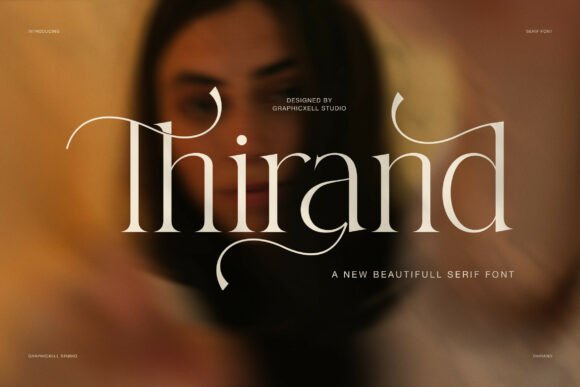
Thirand
Si buscas recursos de alta calidad como Thirand, este paquete premium es una opción fantástica para tus proyectos creativos.
Ya sea que estés creando productos POD (impresión bajo demanda), invitaciones de boda o gráficos para redes sociales, Thirand es una opción ideal.